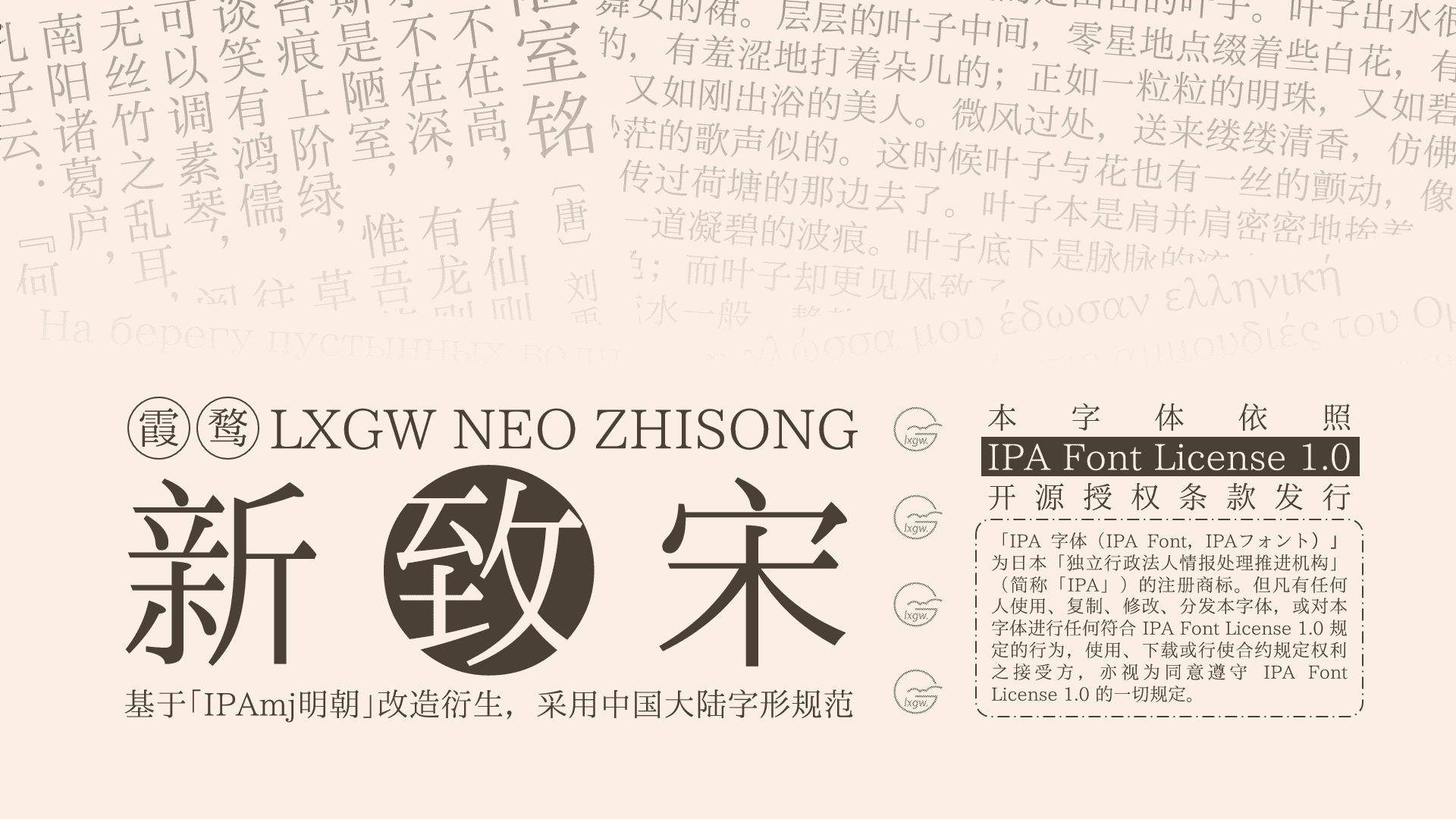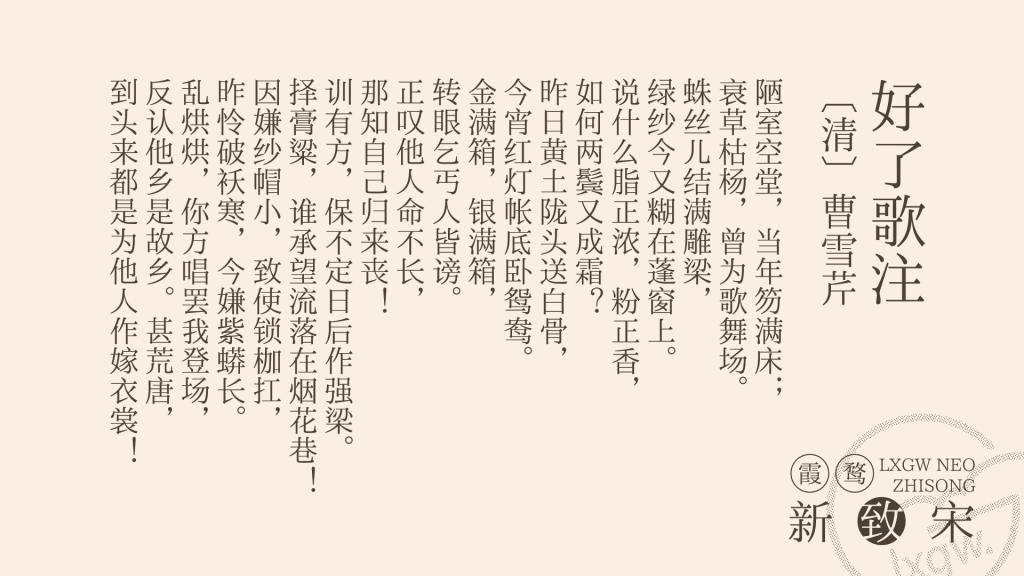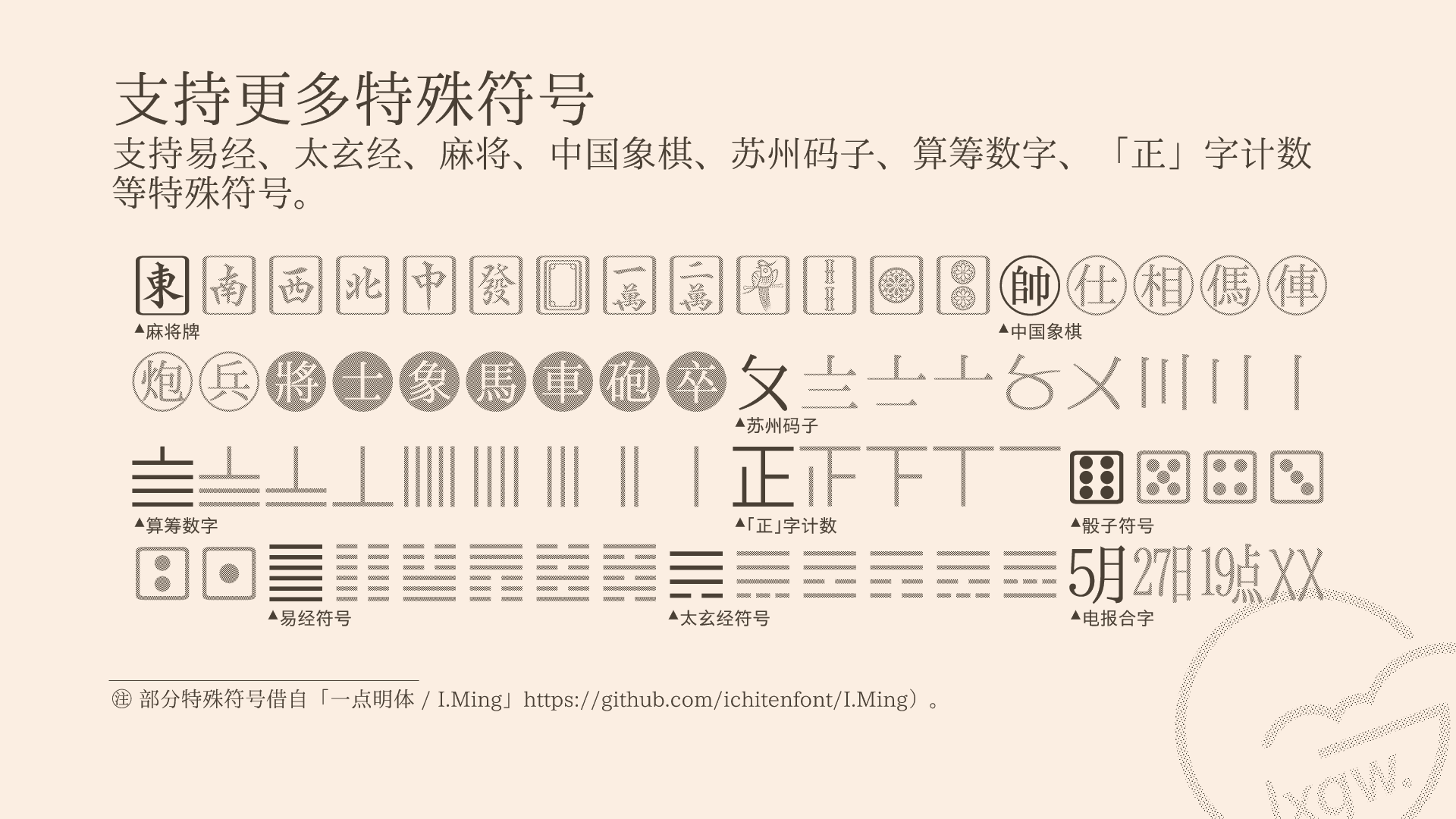
这是一款基于 IPAmj明朝 的中文开源字体,是将日本写法的字体改造成中国大陆规范写法的尝试。
本字体是「霞鹜新晰黑」的姊妹字体,尝试在「IPAmj明朝」原有字形的基础上,将其改造成中国大陆规范字形。
字汇
第一部分(简体为主)
- 现代汉语常用字表 3500 字;
- GB/T 2312-1980 汉字部分 6763 字;
- 通用规范汉字表 8105 字;
- 现代汉语通用字表 7000 字;
- 此外按需添加一些表外字,共分为 5 组,详见外字初步整理表。
第二部分(繁异体为主)
- 港台常用字(包括台湾地区 4808 常用字、香港地区 4825 常用字);
- GB/T 12345-90 汉字部分 6866 字、BIG5 一级(常用) 5401 字;
- 通用规范汉字表附表 1:「规范字与繁体字、异体字对照表」中的繁体字列;
- 外字初步整理表 所含字对应繁体字(主要采用 BabelPad 转换,一少部分为后加,可能存在遗漏);
- 补全 IICore 收录的 9810 个汉字。